公布秘籍前,先让大家Get一个小技能,(如果已经知道的,请低调地直奔正文吧~):在Illustrator、Indesign以及Photoshop中,将文字工具置于两个字母之间,按住Alt / Opt键的同时,按键盘的左右键,即可快捷调整字偶间距噢 >>>
01. 上下颠倒检查字偶间距
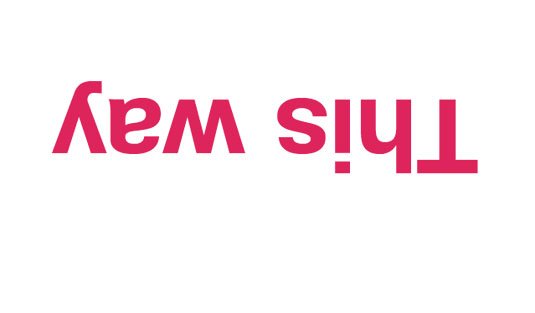
经验证,将字母上下颠倒摆放是有效检查字偶间距的方式。
为何要将字母上下颠倒摆放来查看字偶间距呢?因为这样可以避免你先入为主地阅读单词,有助将字母作为图形来看待,从而更好地审视它们之间的位置关系。当然,如果需要根据词意来对字母进行特殊处理,那么这个方法自然就不适用了。就常规单词而言,这个方法久经验证,是用来检查字偶间距的良方。
02. 模糊处理
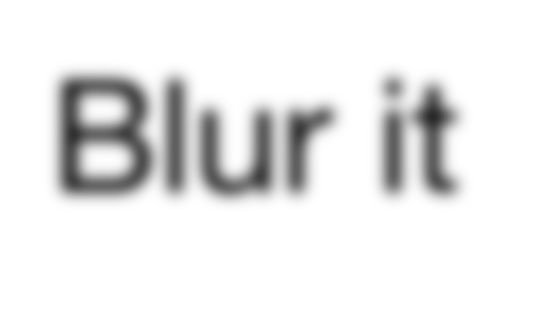
模糊处理后,可以将视觉注意力集中在字体的对比度和留白空间上。
另一个实用技巧就是模糊处理了(或者截屏在PS里做模糊效果,或者微微眯起双眼)。一如 Brian Hoff 在他的文章中所提到过:“我喜欢眯起眼或作斗鸡眼来模糊我的视线,这样可以避免我被单词的含义所影响,将注意力集中在字体的对比度和留白空间上。”这实为一个非常实用的技巧。
03. 用气球填充字偶间距
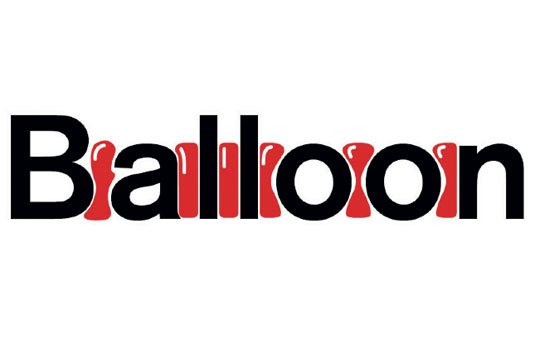
在字母间留出距离,来置入大小合适的气球。
这个方式听起来有些抽象(该想法由设计师 Tom Sewell 提出),就是想象每个字母之间都有个相同尺寸和体积的气球,从而保持字母间的距离。Tom 说到:“要确保气球上下不被挤压,恰好适合字母间所留出的空间。”这个技法很有趣,也很实用。
04. 利用字母“o”来控制间距
另一个小技巧就是靠你的双眸了,确保每个字母前后的空间在视觉上看起来是合理的。一条黄金法则就是想象每个字母间,都端坐着一个“o”(该想法也由 Tom Sewell 提出)。
05. 设置标题间距
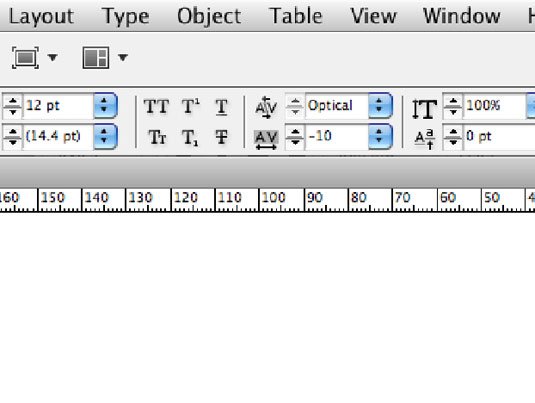
如果你手中在做的是非衬线体标题,那么确保先大致设置字间距,后调整字偶间距。
字间距和字偶间距在标题中最易见,也最好调整。在非衬线字体中,间距问题也暴露得尤为明显。
如果你手中在做的是非衬线标题,那么确保先大致设置字间距,后调整字偶间距。如果几乎每个字母的字偶间距都需要在-10,可先将字间距统一调整为-10后,再进行逐一调整。
这个方法同样也适用于数字。好比数字“1”以及其前后的数字,或是空格关系,例如:’213’,1和前后两个数字的字偶间距相对需要紧一些。如果是“11”,那么字偶间距就要十分紧凑了。
06. 切勿缩放大写字母
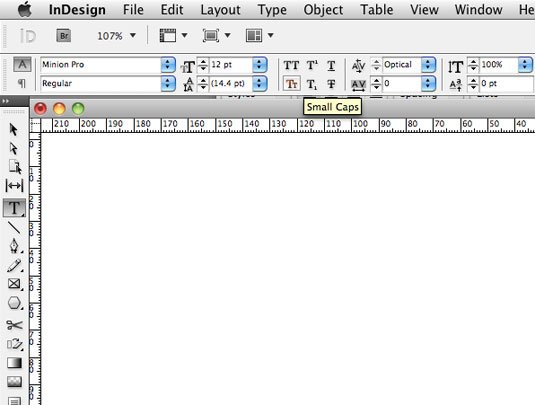
千万不要缩放大写字母后,称其为“小写”。
John D Berry 是多本有关字形与字体书籍的作者,要问他最有用的诀窍是什么?回答是:除非你清楚真假小型大写字母间的区别,最好别用设计软件里的那个选项。千万不要缩放大写字母后,称其为“小写”,因为它们并不是。如果你非要自寻烦恼地选择使用小型大写字母,那么确保正确设置字间距,它们通常需要比小写字母的间距宽松一些。
07. 勿用过多字体
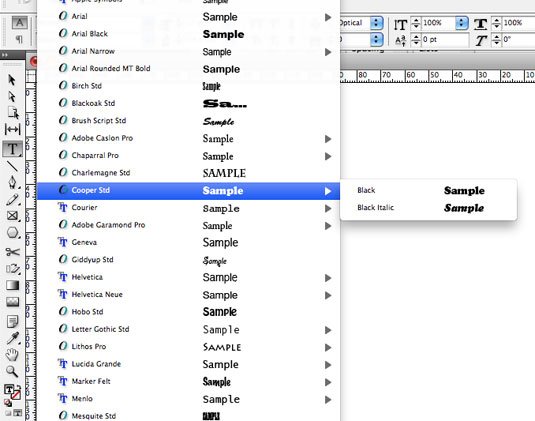
控制选用的字体种类,可以使版面清晰简洁。
要将字体视为设计项目整体中的一部分,这点很重要。当使用的字体超过三种时——也许同时有粗衬线体、非衬线体以及展示体,这样很可能造成内容不易读或不被易理解,从而导致项目缺乏秩序感。每款字体通常都有不同粗细供选用,将其正确组合使用,便可以在打造简洁设计的同时,不失层次感,呈现清晰锐利的视觉效果。所以,好好考虑,是非要很多种字体呢?还是选用一种字体,用不同的粗细来打造一个有效的设计?要感谢 Hey Studio 提供的这个建议。
09. 不要令字体变形(除非你有意为之)
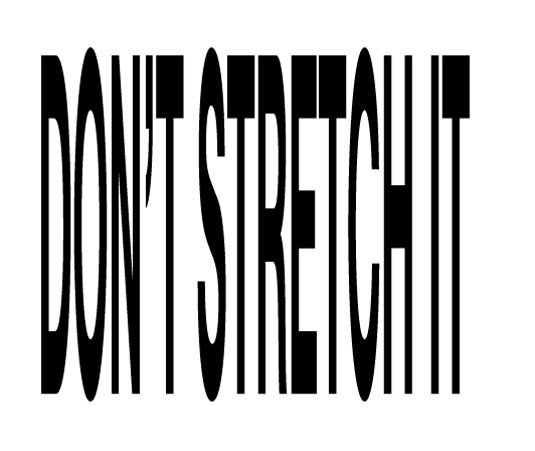
如果要将字体变形,确保你有充足的理由要这么做。
除非是要制造特殊效果(或进行插画制作),不要随意拉伸、扭曲或在转曲线后窜改字体外形比例。想象一下,你应该不会扭曲一张照片或矢量图,因为这很有可能造成极不美观且不专业的后果。如果要编辑一个字体外形,确保有充足的理由,肯定自己不会毁了字体设计师日以继夜的辛勤成果。
10. 字体是一种声音
该有趣的概念来自 Hoon Kim (Why Not Smile),他提到:“对字体的把握就好比对声线的掌控:对字体的取舍就如同对音质的选择;字母之间的关系就好比音色的大小、数量和不同音阶;字体的排版犹如声音之于时间和空间。排版设计视听兼备,如果你有一个好故事,那么,是时候选用好演员了。”
备注:
字偶间距(Kerning)是根据相邻字母的关系来调整间距,也就是“审美间距调整”。
字间距(tracking)是无视具体字母的“字符间距调整”。